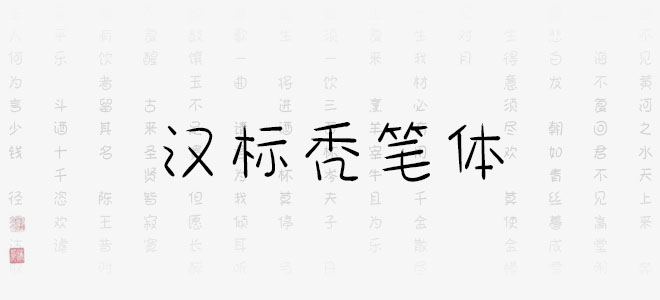
漢標(biāo)禿筆體字體是漢標(biāo)字庫(kù)中的一款藝術(shù)字體,通常字形中的點(diǎn)、撇、捺、鉤、提等筆畫各具面目,筆畫運(yùn)用了禿筆元素來構(gòu)建,把這些筆畫做成了禿筆,概括為飄逸的禿筆,并且使左右舒展的筆畫盡量對(duì)稱,最大限度地簡(jiǎn)化筆畫禿筆造型。歡迎喜歡漢標(biāo)禿筆體字體的朋友前來下載使用。
漢標(biāo)禿筆體